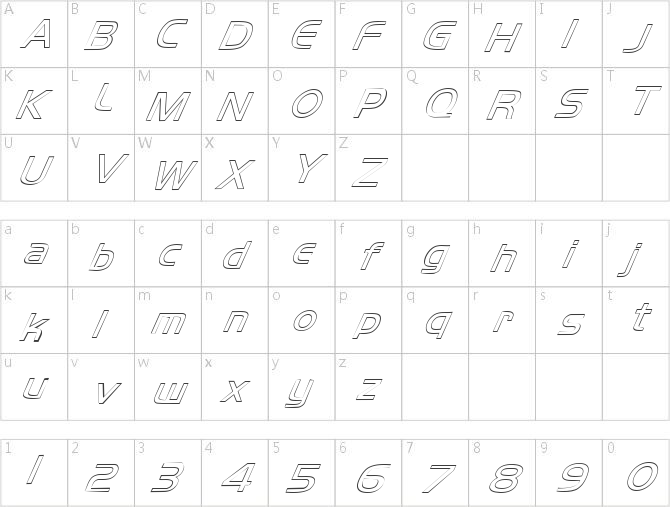
FZ BASIC 8 HOLLOW ITALIC
FZ BASIC 8 HOLLOW ITALIC字體字庫是一款讓人賞心悅目、百看不厭的英文字體,適合各類廣告和產(chǎn)品包裝設(shè)計應(yīng)用,字體大小0.07MB,格式為ttf字體,上傳用戶是Bot,作者/版權(quán)方為未知